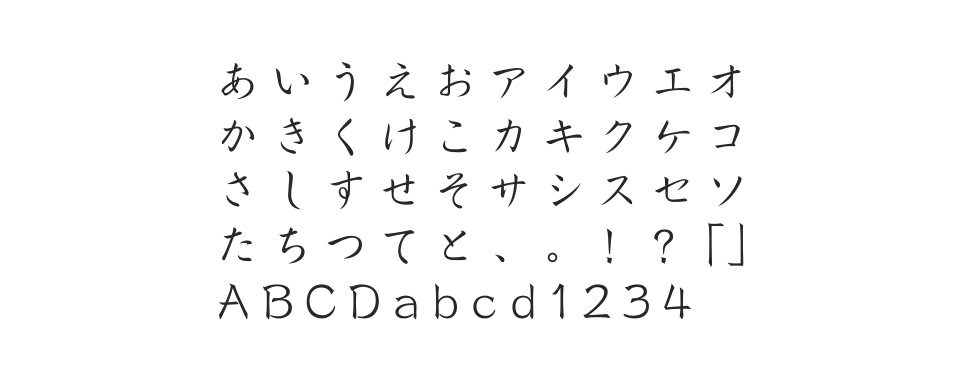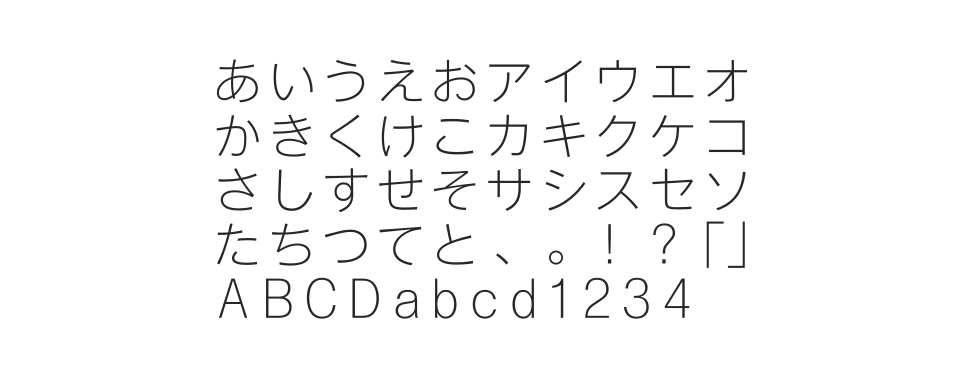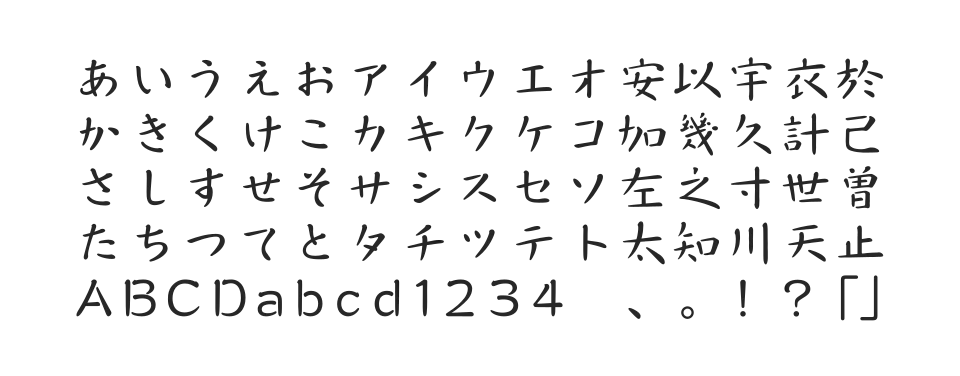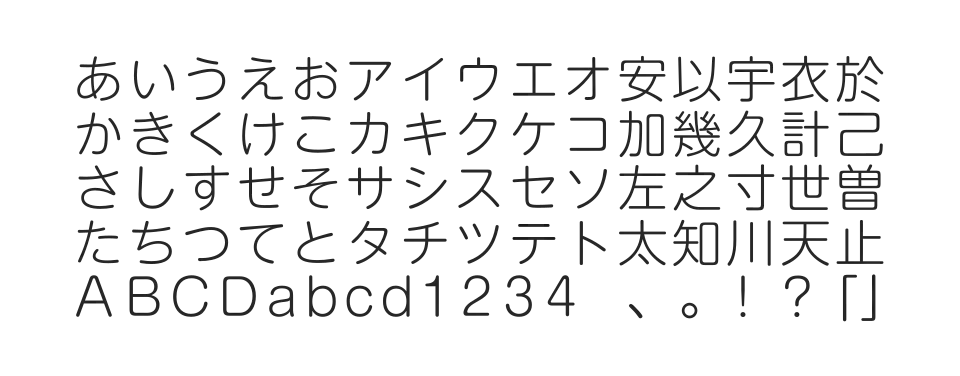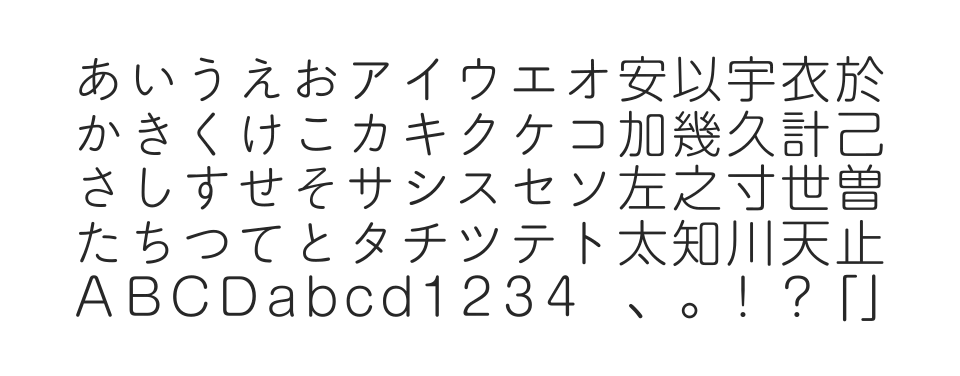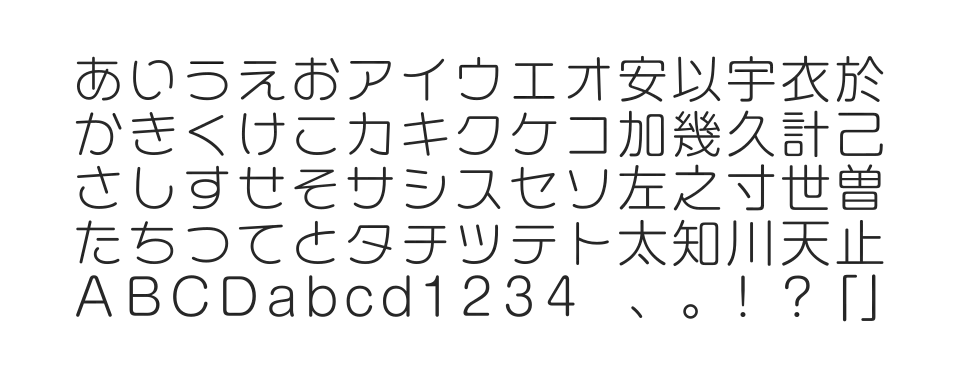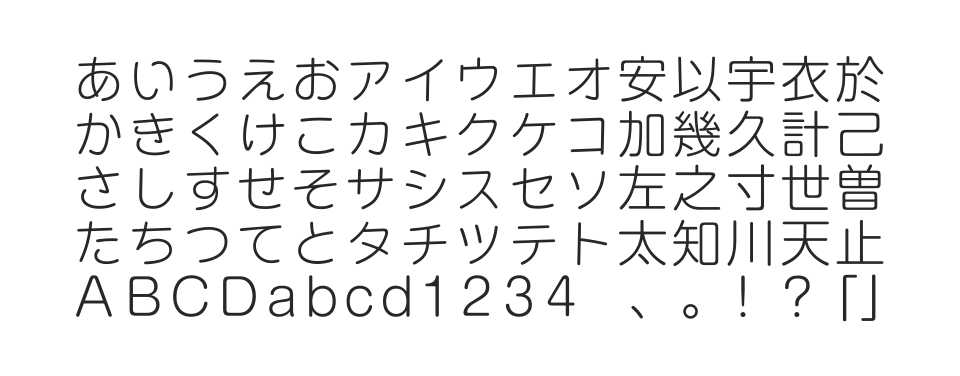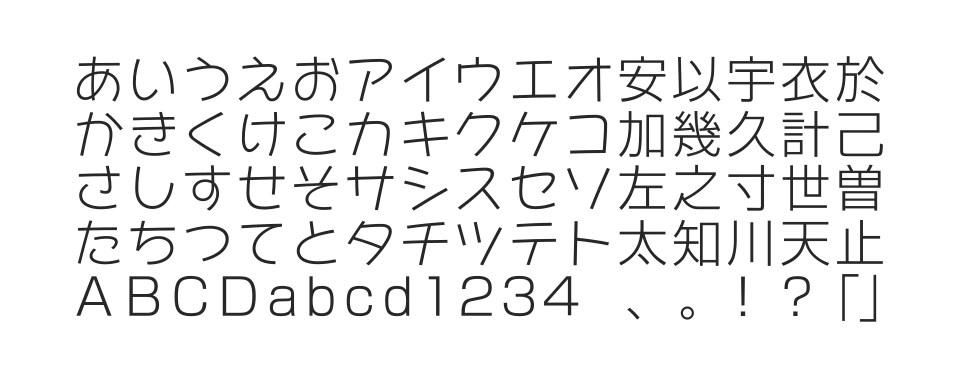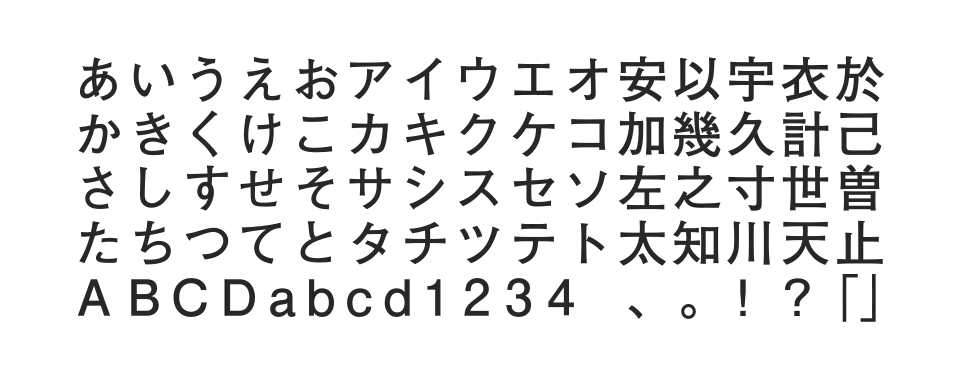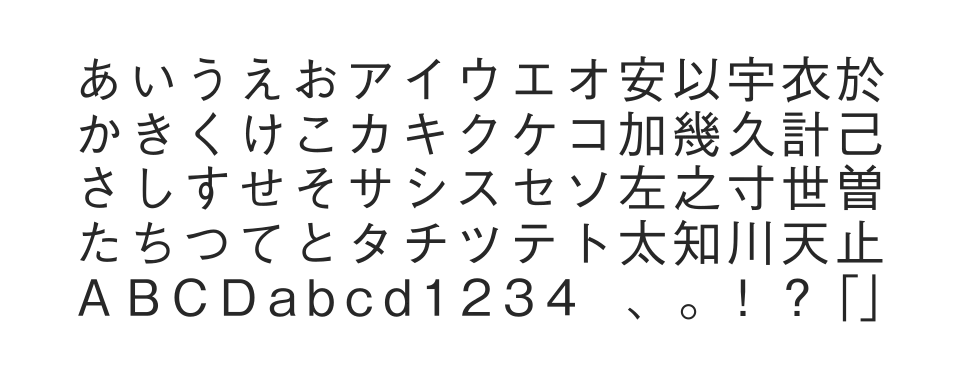
基本的な書体として長く愛されてきた伝統的なゴシック体。オーソドックスな字形に、アクセントのあるエレメントをもち、文字の大きさは全角に対してやや小さめで可読性と安定感が良好です。
活字書体のデザインを忠実に引き継ぐゴシック体。縦画には打ち込みのアクセントがあり、縦横の画には視認性を考慮した抑揚があります。モリサワ基本7書体の一つとして広範囲に使われています。
若々しい笑顔を思わせる親しみやすさが持ち味のゴシック系のかなに、「新ゴ」の漢字や英数字を組み合わせた書体。丸文字やPOP書体の流れをひきついだ、やわらかく気どりのない表情が特徴です。
手書き文字のようなあどけなさが持ち味のかな書体。やわらかく親しみやすいストロークのなかに、やや右上がりの動きが感じられ、すっきりとしたイメージを持っています。
丸いエレメントが楽しいポップな丸ゴシック系のかなに、「新丸ゴ」の漢字や英数字を組み合わせた書体。手書き文字風のデフォルメされた形が、子供っぽさやかわいらしさ、楽しさを演出します。
モリサワの丸アンチック体フォントファミリー。7つのウェイトを持つ丸みのある書体で、温かみのある親しみやすいデザインが特徴です。
モリサワの丸ゴシック体フォントファミリー。7つのウェイトを持ち、親しみやすく読みやすい丸みのある文字デザインが特徴の書体です。
モリサワの個性的なフォント。独特の文字デザインが特徴で、アート作品やクリエイティブなデザインに適した印象的な書体です。
モリサワのゴシック体フォントファミリー。16のウェイトを持つ豊富なバリエーションで、様々なデザインニーズに対応する現代的な書体です。
モリサワの上品なかな書体。流麗で美しいかな文字が特徴的で、和風デザインや高級感のある文章表現に適したフォントです。